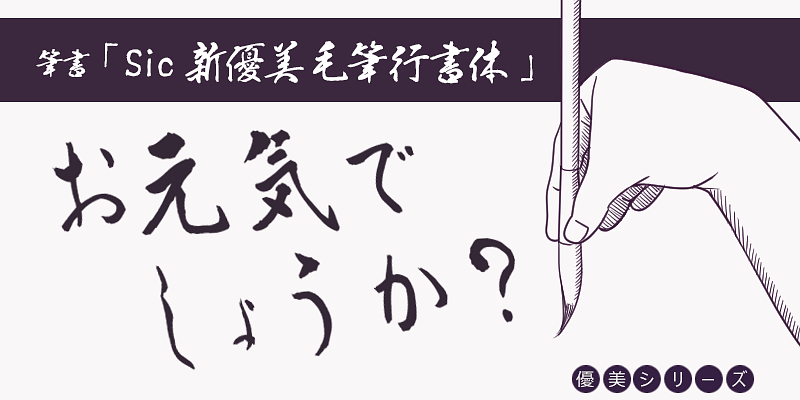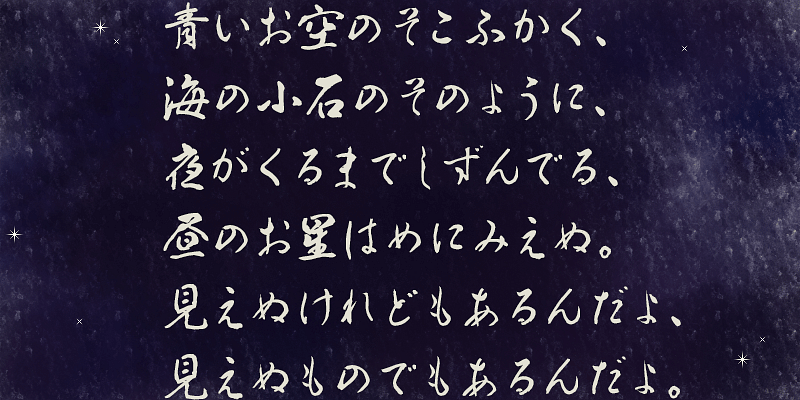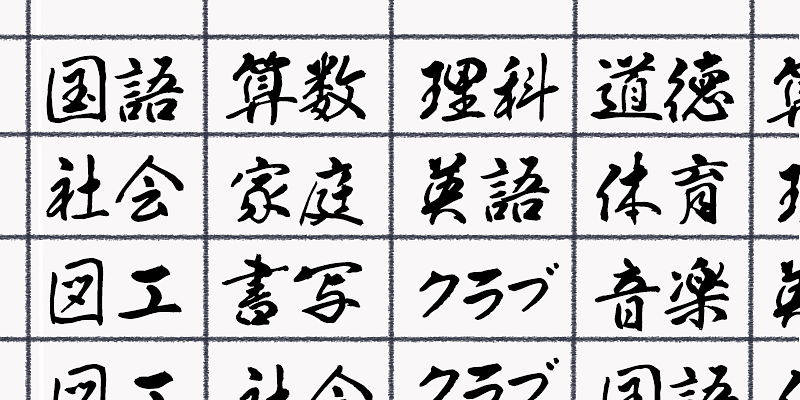
Dès son plus jeune âge, Eiichi Kawazoe a étudié la calligraphie sous la direction de son père. Au département de calligraphie de l’université, il a appris les kanji auprès de Kiseki Kosaka et Toson Amaishi, ainsi que les kana auprès de Kitsunan Tanibe et Kayu Hirata. Pour perfectionner son apprentissage de la calligraphie japonaise fluide des kanji et kana, initié par Yukinari, il a rassemblé de nombreux documents anciens. Il continue de perfectionner ses compétences afin de préserver les caractères traditionnels japonais qui se sont développés parallèlement à l’ukiyo-e. Il écrit également des sceaux utilisés dans les sanctuaires et des cartes pour l’art du rakugo, et se lance des défis avec les caractères utilisés dans le sumo et le kabuki.